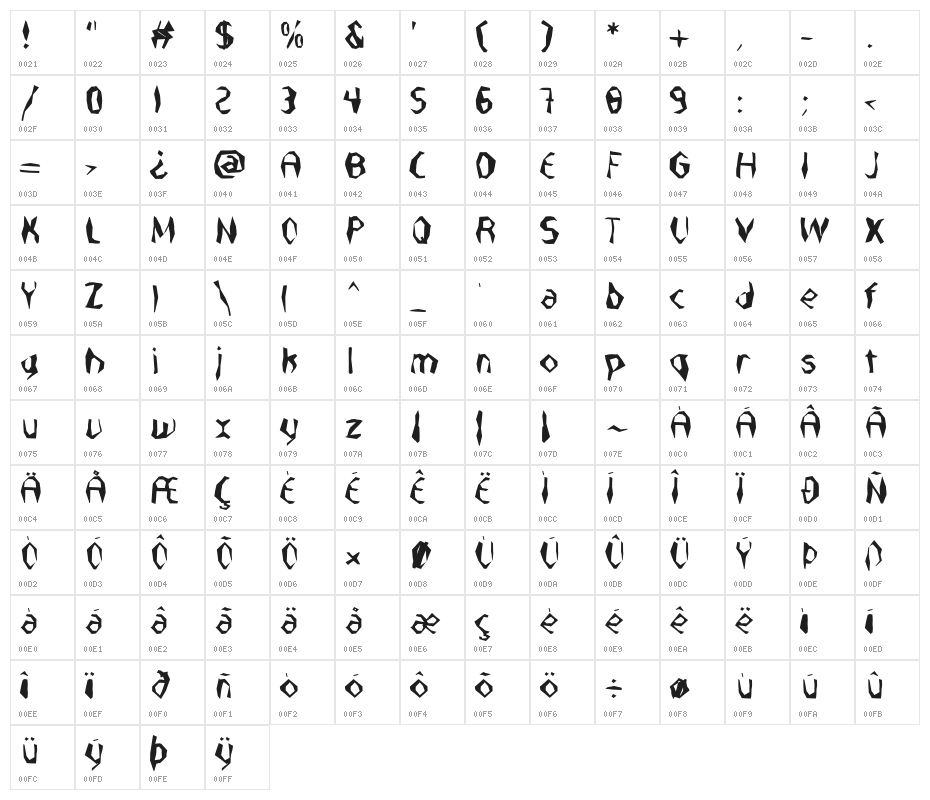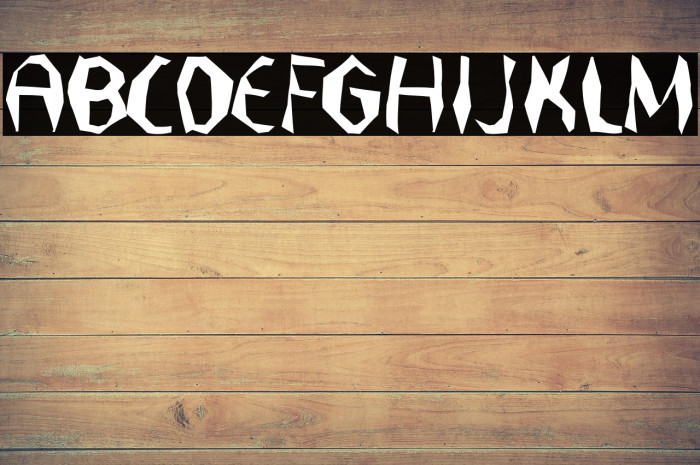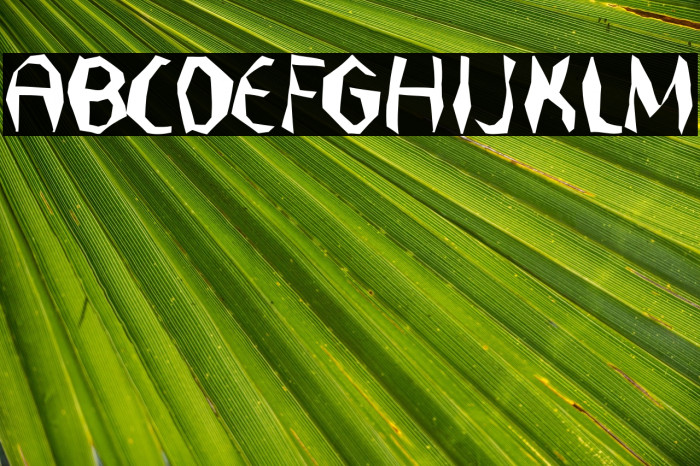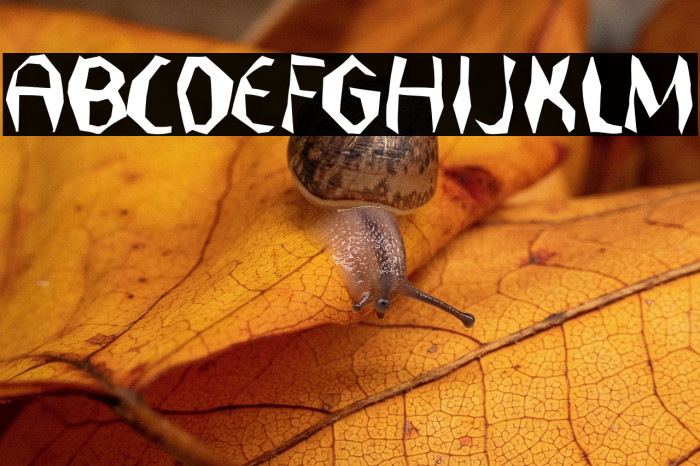
Nabatea Font
| Progetti proposti | Ideal for projects requiring a bold, artistic touch, such as posters, album covers, or branding for edgy or alternative products. |